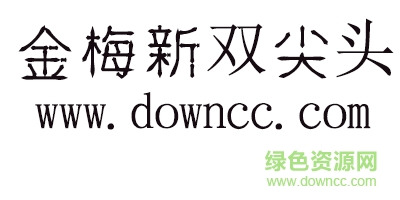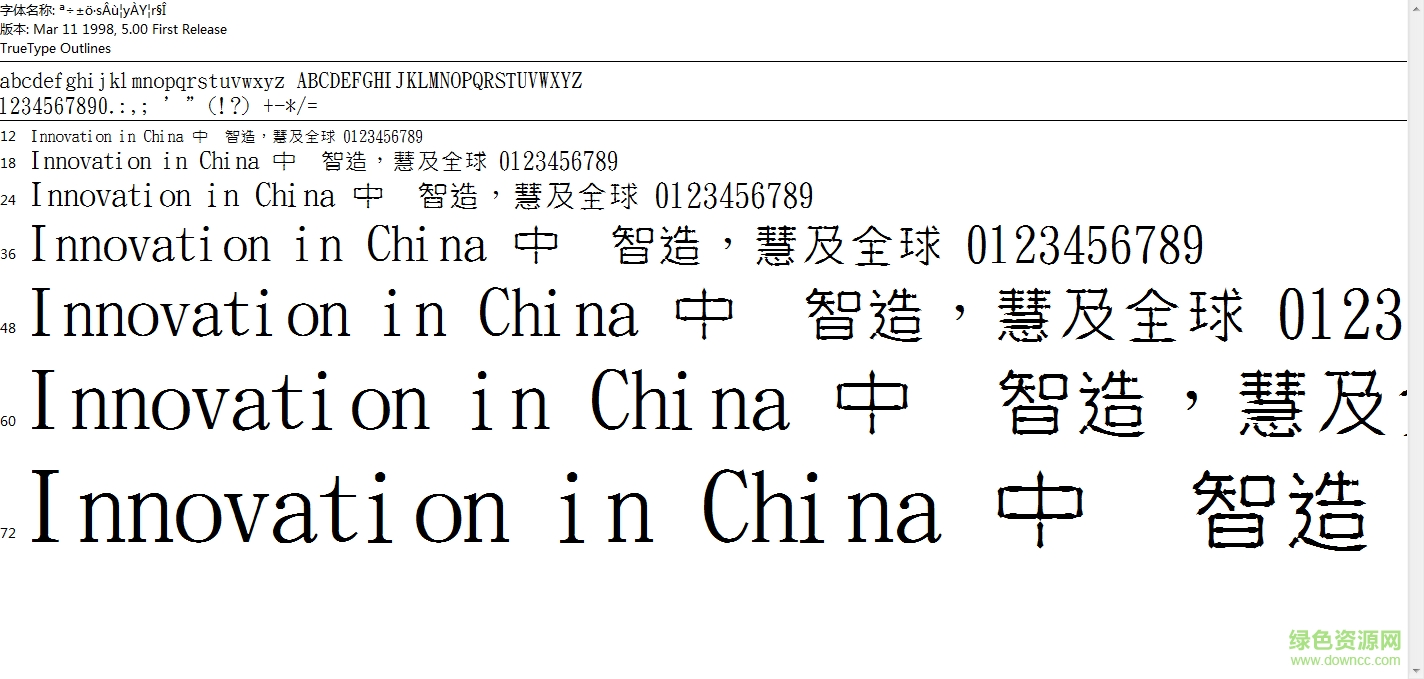
金梅新雙尖頭字體外形很美觀大氣!這款字體比較適合設(shè)計(jì)廣告、海報(bào)。可以在win7、win8等系統(tǒng)上安裝使用!輸出的文字效果非常好!趕快來本站下載安裝吧。
金梅新雙尖頭字形是一款非常美觀的金梅字體,此款字體字型優(yōu)美,應(yīng)用范圍廣泛,可直接導(dǎo)入至ps中,支持中文、英文、漢字輸入,歡迎來綠色資源網(wǎng)下載使用!